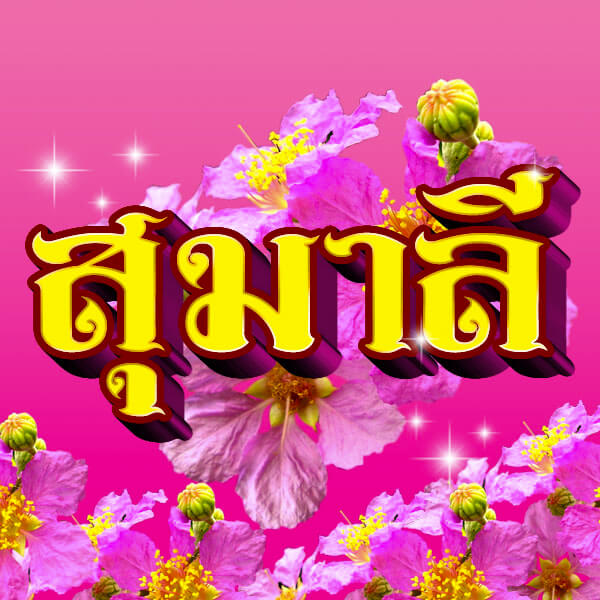
ผมทำงานอยู่ “ร้านป้ายศุภณัฏฐ์ (ศิลป์เจริญ)” อยู่อำเภอโพนทราย จังหวัดร้อยเอ็ด แรงบันดาลใจในการทำงานก็คืออยากให้เกิดฟอนต์ที่เข้ากับงานไทยๆ ก็เลยคิดทำขึ้นมา สำหรับชื่อ ฟอนต์ “สุมาลี” คือชื่อภรรยาครับ
ตัวอย่างที่ใช้ในงานป้ายครับ
เบื้องหลังการออกแบบ: ฟอนต์ สุมาลี
สุมาลี (NPK-Sumalee)